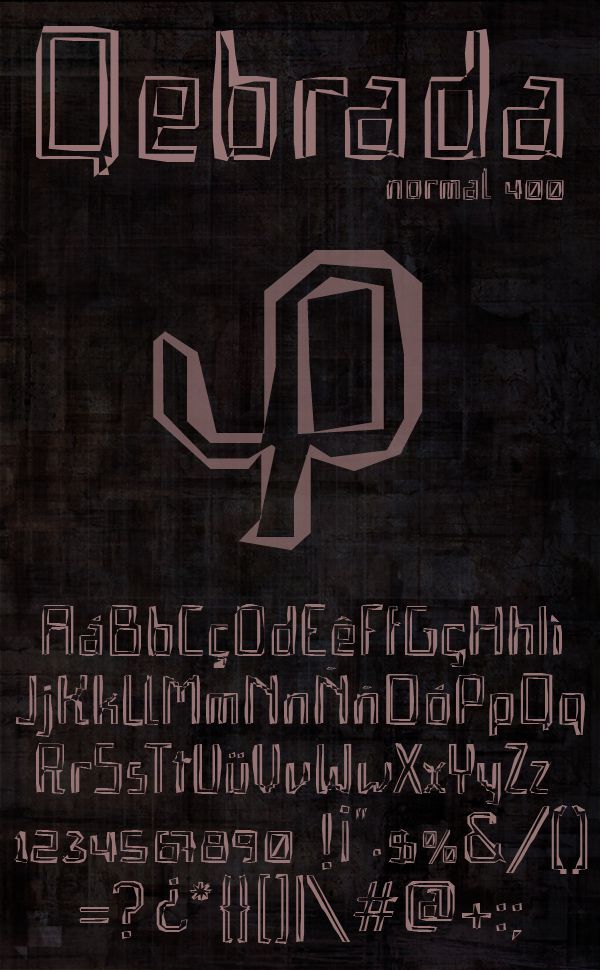
Шрифт Qebrada
Esta fuente es un experimento de deconstrucción hecho a partir de un nuevo proyecto tipográfico en el que trabajo basado en la secuencia de Fibonacci y Lucas. La fuente dispone de todos los caracteres latinos, opciones Open Type y Kerning. Website: defharo.com